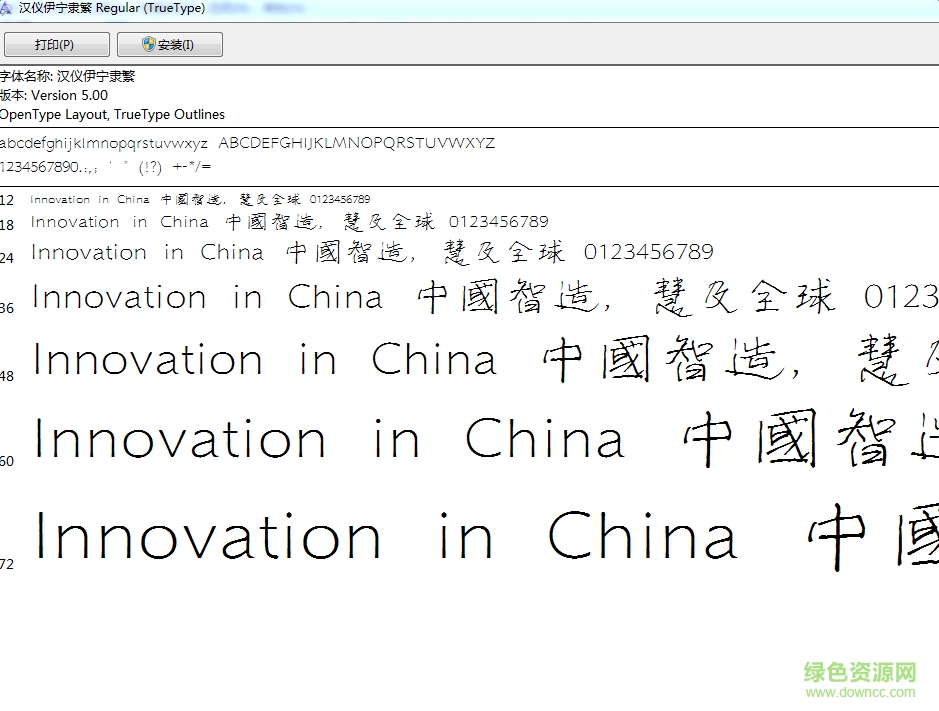
漢儀伊寧隸字體是一款漢儀類古典繁體風(fēng)格字體軟件,伊寧隸完美闡釋了隸書的優(yōu)雅姿態(tài),添上些許行書的元素,十分優(yōu)美好看,還有更多好看的字體歡迎來綠色資源網(wǎng)下載使用!
漢儀伊寧隸是行書與隸書的融合體,書寫講究特征,具有行書的流暢、瀟灑、隨意與隸書的雅致,特征為:樸拙、流暢、隨意、雅致而又不失講究。適用于廣告設(shè)計(jì)、平面設(shè)計(jì)、印刷包裝、藝術(shù)設(shè)計(jì)、網(wǎng)站設(shè)計(jì)領(lǐng)域。
此字體筆畫細(xì)膩行如流水,配上古典繁體字,文雅氣息十足,適用于設(shè)計(jì)方面哦!還能在親友面前裝一波文雅!